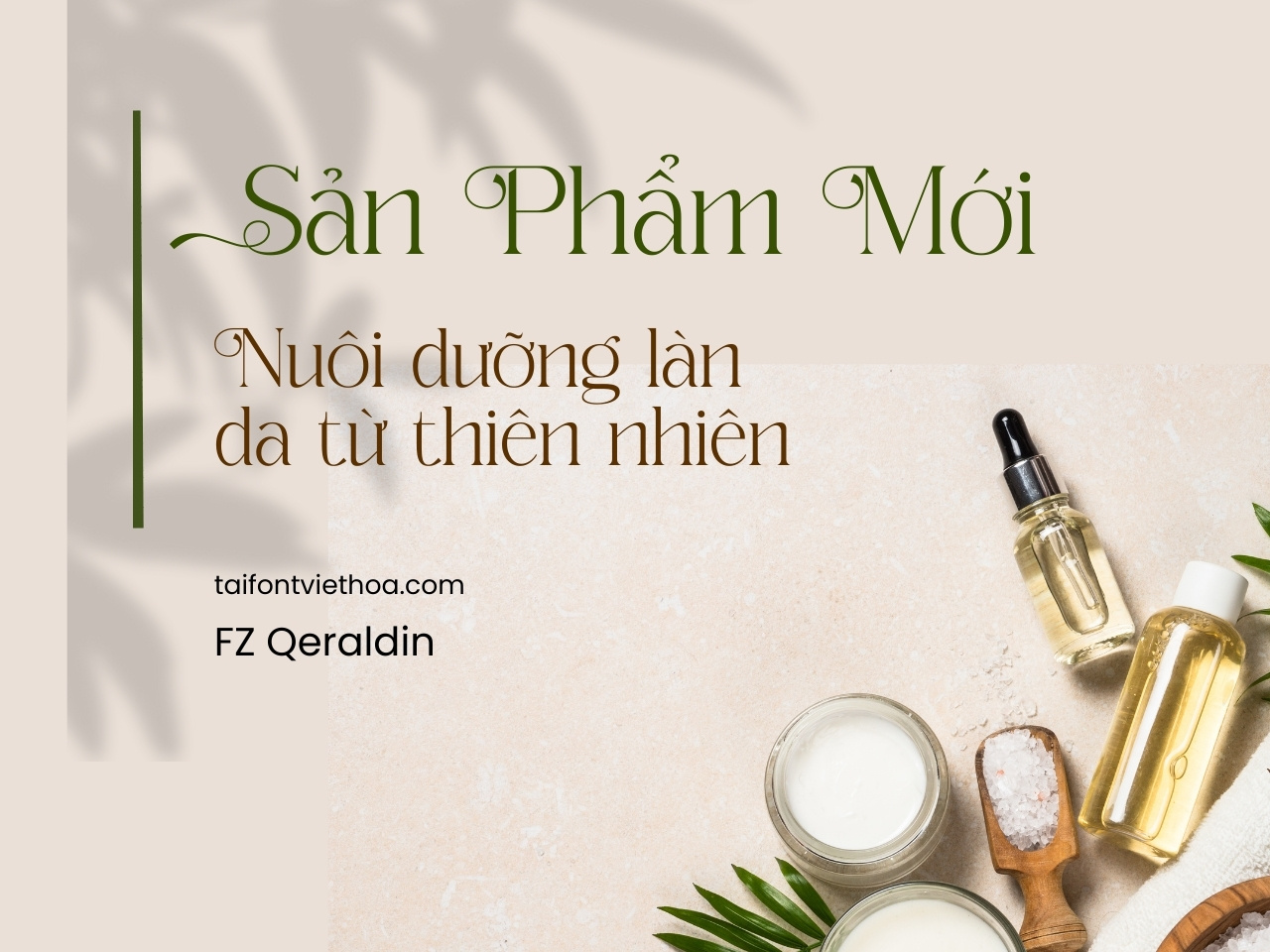
Font việt hóa Fz-Qeraldin
Tác giả Font: Letterena Studios
Giới thiệu font Fz-Qeraldin – Thanh lịch và mềm mại từ Letterena Studios
Fz-Qeraldin là một font serif hoa mỹ được thiết kế bởi Letterena Studios – đơn vị nổi tiếng với các font mang phong cách cao cấp, nữ tính và trang trí tinh tế. Font mang hơi hướng cổ điển châu Âu, được thể hiện qua các nét cong uốn lượn và độ tương phản sắc nét giữa nét thanh – nét đậm. Phiên bản Việt hóa do FontZin thực hiện, hỗ trợ đầy đủ tiếng Việt và hơn 100 ngôn ngữ khác. Đây là một lựa chọn lý tưởng cho các nhà thiết kế đang tìm kiếm sự thanh lịch, dịu dàng nhưng vẫn nổi bật trong truyền tải thông điệp thương hiệu. Font đã được taifontviethoa.com chọn lọc và giới thiệu như một giải pháp tối ưu cho các thiết kế nghệ thuật và thương hiệu cao cấp.
Đặc điểm thiết kế nghệ thuật và ứng dụng của Fz-Qeraldin
Fz-Qeraldin nổi bật với các chi tiết serif được cách điệu mềm mại, các đường nét uốn lượn giúp truyền tải sự uyển chuyển và quyến rũ. Các chữ cái có hình dáng cao, thanh mảnh với phần đầu chữ được nhấn nhá tạo nên phong cách thời trang, hiện đại mà không mất đi sự cổ điển. Font rất phù hợp cho các thiết kế bìa sách, logo boutique, thương hiệu mỹ phẩm, thiệp mời, tiêu đề trang web và poster sự kiện nghệ thuật. Các ngành nghề ứng dụng lý tưởng gồm ảnh cưới, giáo dục, mỹ phẩm, thời trang cao cấp, và đặc biệt trong các dịp như Trung thu, sinh nhật, lễ kỷ niệm hoặc chiến dịch hướng đến phái nữ.